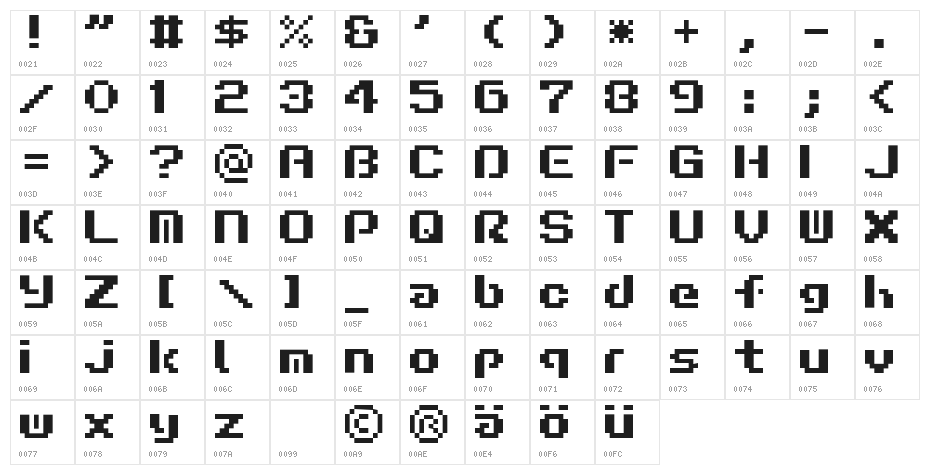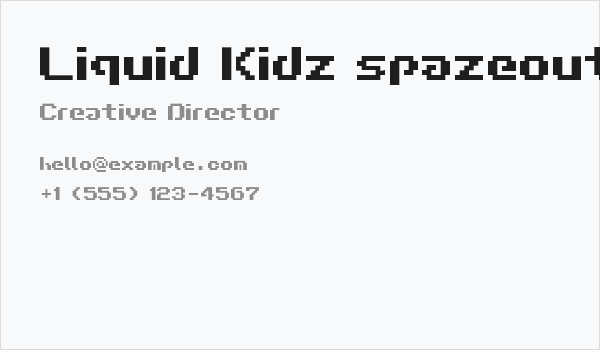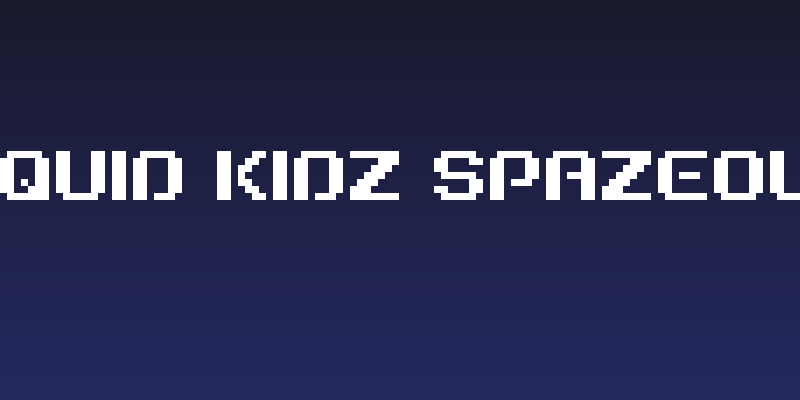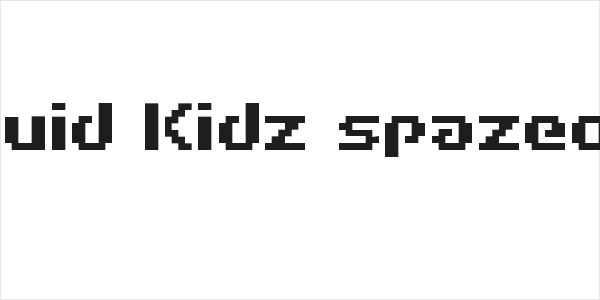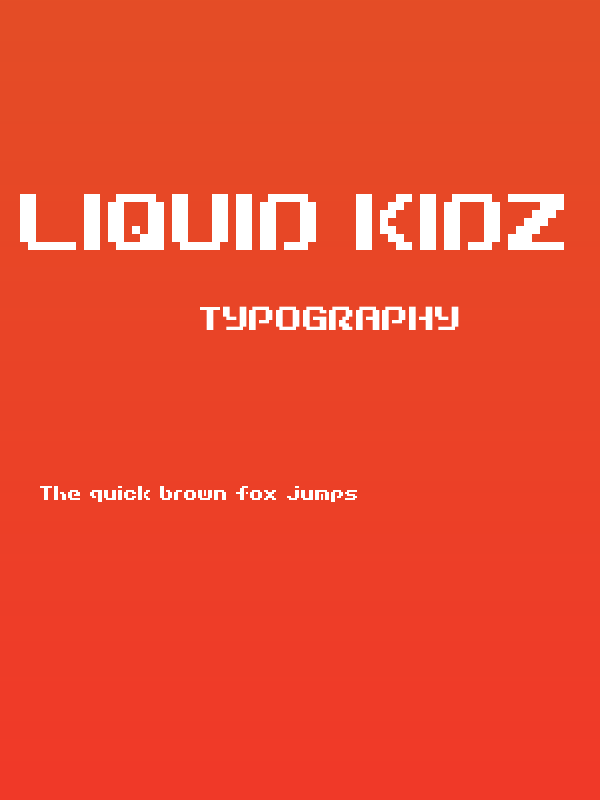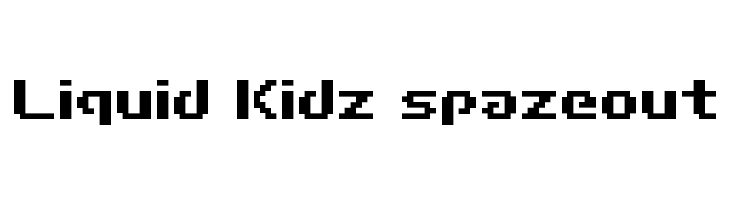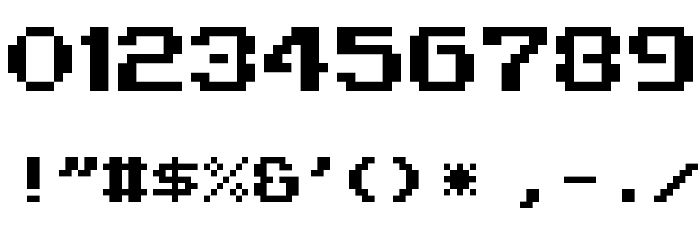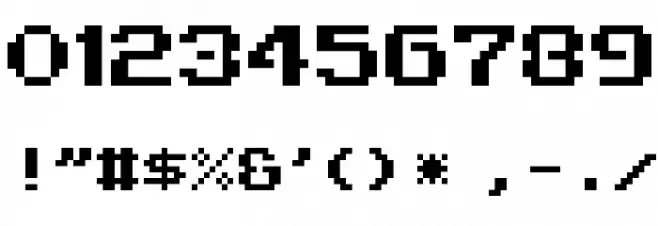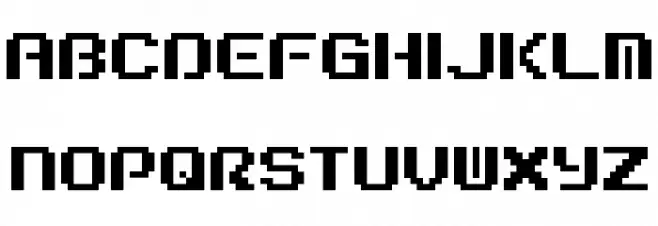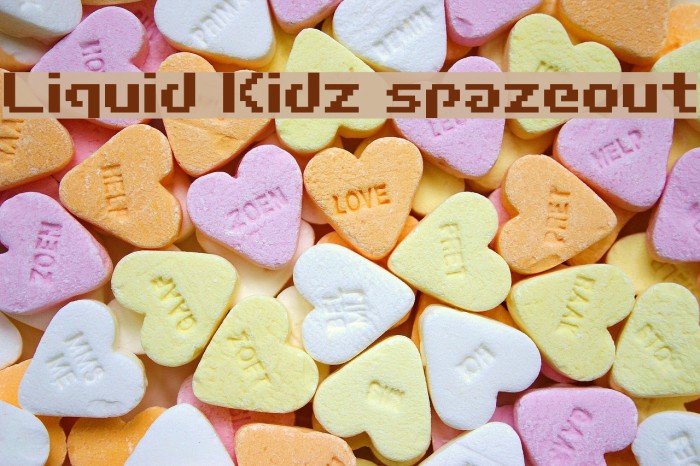
Liquid Kidz spazeout Font
✎ Pixel
| Catégories | Pixel |
| Style général | Retro, Digital |
| Projets proposés | Ideal for video game graphics, tech-themed posters, digital art, and retro-inspired branding. |